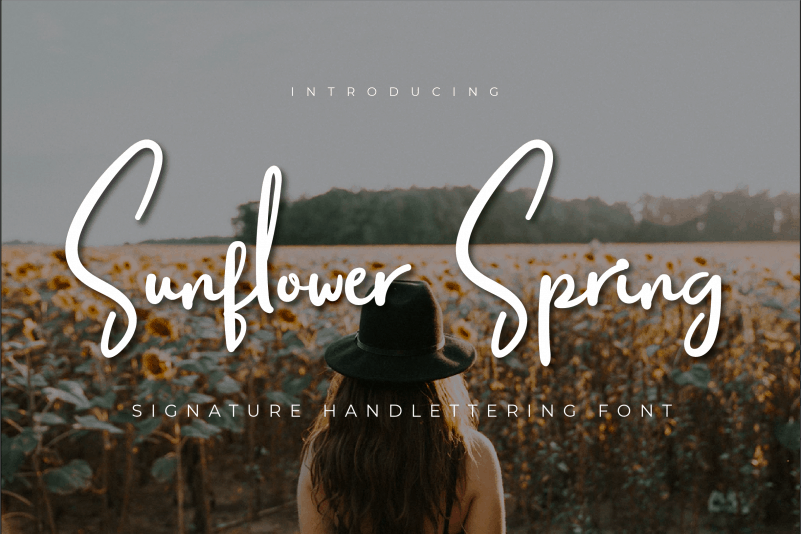
A Sunflower Spring Script Font é uma elegante fonte feita à mão que transmite uma mistura única de sofisticação tipográfica com modernidade e frescura. Inspirada na flor dourada das abelhas, esta fonte traz um toque de simplicidade que se conecta perfeitamente com os dias atuais sem perder seu encanto tradicional. Perfeita para projetos que buscam uma identidade visual única e sofisticada, a Sunflower Spring Script Font é uma escolha inteligente para quem valoriza tanto a qualidade quanto o design contemporâneo. Descubra como esta fonte pode revolucionar a forma como você expressa sua marca ou criado.